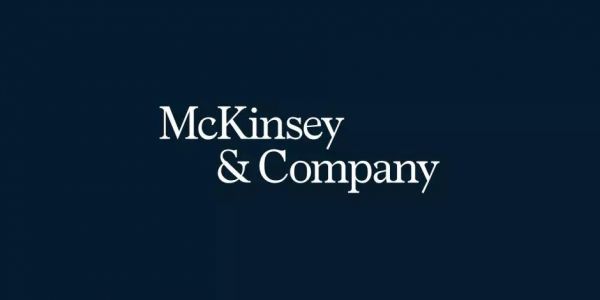
咨询巨头麦肯锡换LOGO,就只“敲了个回车键”?
昨天,正当大大君觉得世界太安静的时候
老铁的爆料让我精神一振:
全球第一的管理咨询公司
麦肯锡换新LOGO了,还更新了全套的视觉系统!
从原本的深蓝色字体“小长条”
变成了这样!
咦……?
这是设计师不小心扣了个回车键
就直接保存交稿了么?
其实麦肯锡原来的LOGO已经相当成熟
优雅的衬线字体,字母“y”的尾部被适当加粗
字母间的间距、大小、粗细处理恰当
视觉效果很舒服
而新LOGO最直观的变化
是字体排版从一行变成两行
“& Company”被移至下方后三分之一的位置
除此之外,字体设计也发生细微变化
在沿用衬线字体的基础上,加粗了笔画
衬线部分也随之加厚,字母“y”的尾部回归直线
整体看上去厚重了不少,但依旧保持高度协调
虽然字体看上去只是被细微调整
但其实这是麦肯锡为更新视觉系统
特地打造的一套全新字体“Bower”
并且形容它“大胆、具有个性”
从放大的动图来看
字体的设计精髓在于其衬线部分
磅数更大,弧度也比原来字体更小一些
所以视觉上会有衬线变厚的感觉
另外,LOGO颜色延续了麦肯锡一贯的蓝色
但同时“麦肯锡蓝”变成了更深的蓝色
麦肯锡称它们为“高对比配色方案”
更深的蓝色得以与白色形成鲜明对比
以更强的视觉冲击力让受众的视线更集中
避免受到其他“视觉杂质”的打扰
同时推出了相应的辅助配色
蓝色和青色的饱和度都十分之高
更加突出“高对比”的配色效果
麦肯锡的商业PPT模板因为独特的思维方式
一直被奉为“业界典范”
那么这个新的配色系统
应该是要为PPT增添更有张力的视觉效果吧
不过设计师表示,这样的配色和排版方式
已经引起了我的极度舒适
除了新的LOGO设计之外,还有新的辅助图形
即是一组扭曲拧转的细线光束
不断扭动形成不同造型
即使作为静态图片来看,也带有律动感
新的LOGO、配色、字体以及辅助图形
已经在麦肯锡的视觉系统中得到充分的应用
麦肯锡的英文官网也已经随之更新
在UI设计方面增加了更多动态效果
体现数字化和科技感
针对这次视觉系统的更新
还有一个极具动感的宣传视频
不得不说,论“高逼格”
还是麦肯锡会玩啊
不过手动@麦肯锡
是不是也要考虑更新一下
大中华区的官网设计呢?
对于麦肯锡这个名字,相信很多人都觉得耳熟
也知道这是一个全球有名的管理咨询公司
而麦肯锡作为全球领先的咨询公司
在此时更新设计,首先是为了更新品牌自身的形象
基于在设计、数字和分析等领域的新业务
数字化的时代特征需要在视觉上有所展现
另外,也有可能是表现咨询公司行业
正在慢慢进入新阶段——
正如麦肯锡的新LOGO既保留原LOGO的优雅气质
又增添了现代设计趋势的设计手法
对于新LOGO,国外网友的评价
还是比较正面的
但认为在具体应用上略逊一筹
而国内的网友对于新LOGO的看法
有好:
也有坏:
对于很多非设计师的网友来说
这样的LOGO改动相当于
“重新排了个版”
或者是“按了个回车”
那按着这个逻辑
麦肯锡的下个LOGO可能是这样的:
1. 换个排版
2. 来个竖版
3. 或者,再打多一个回车……?